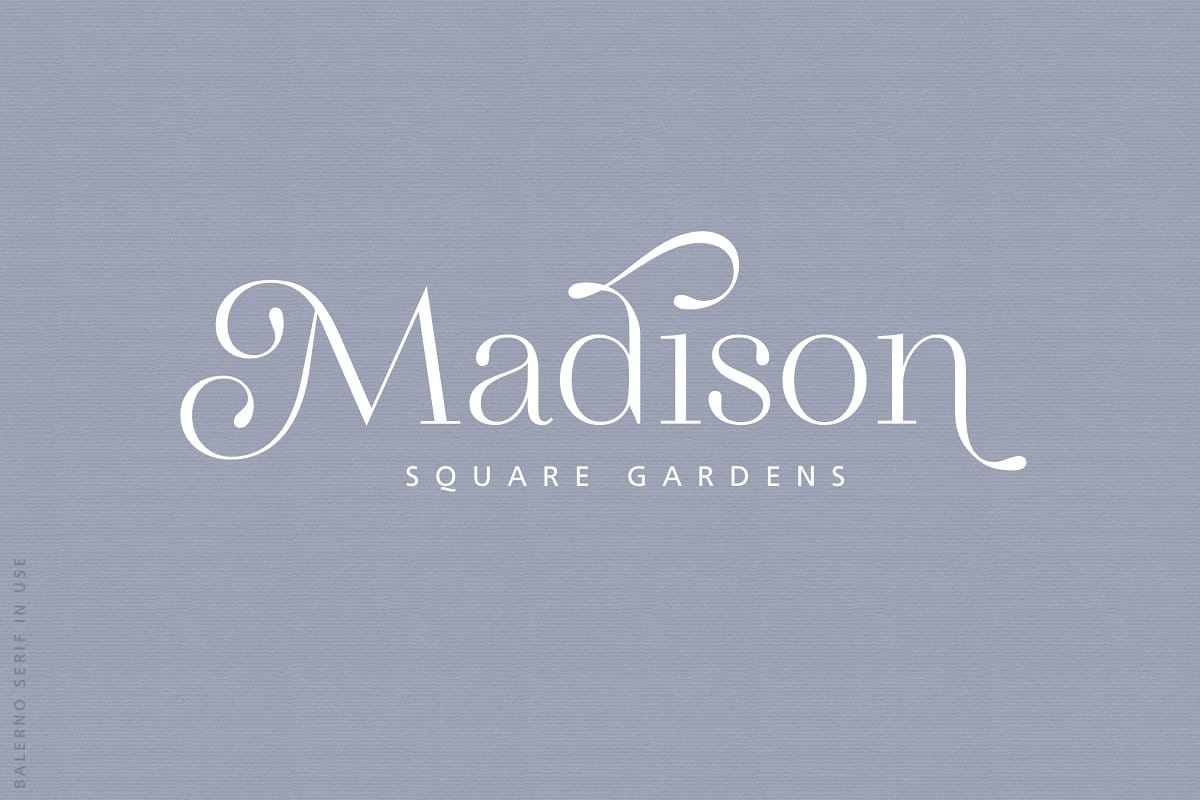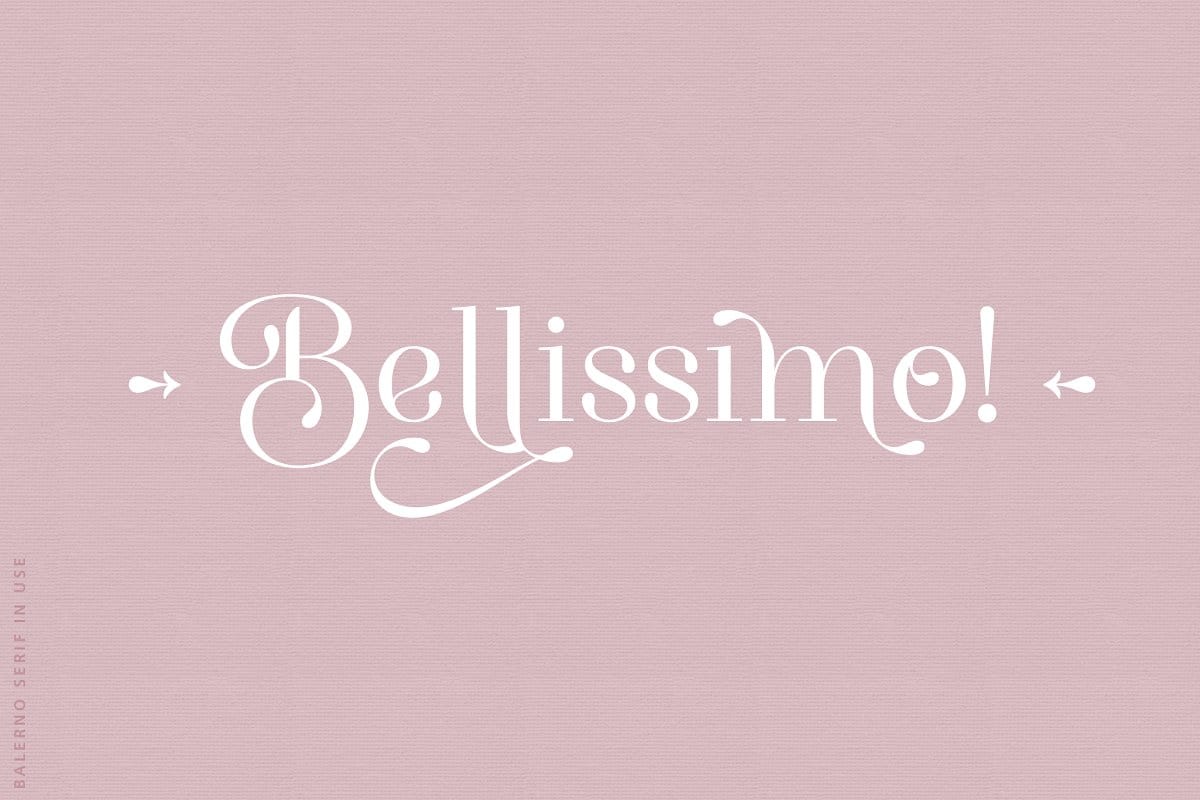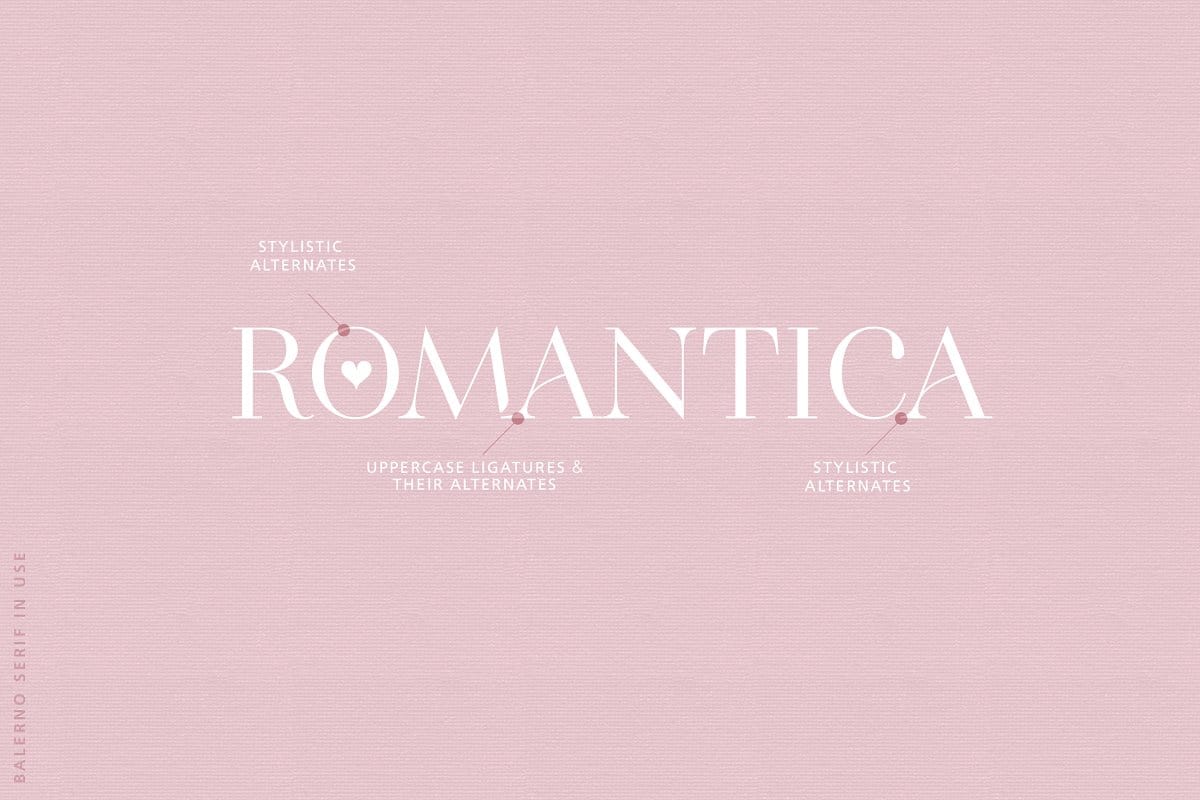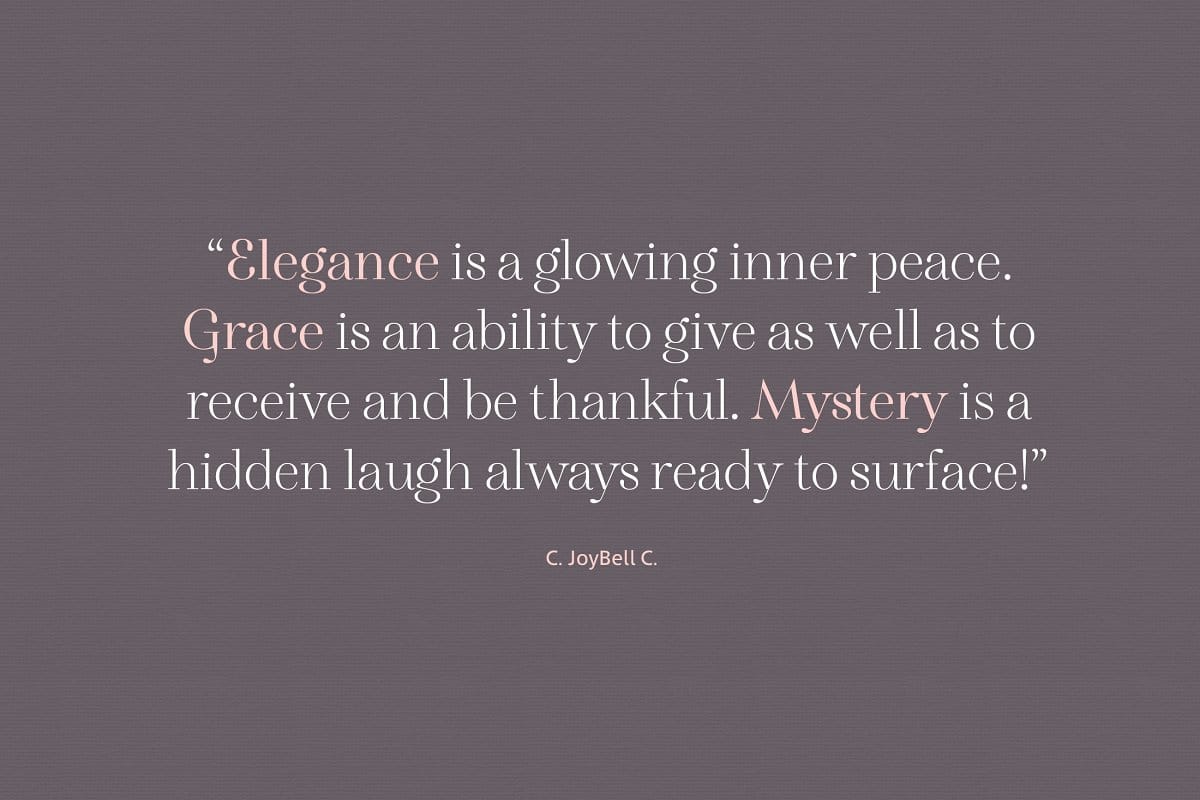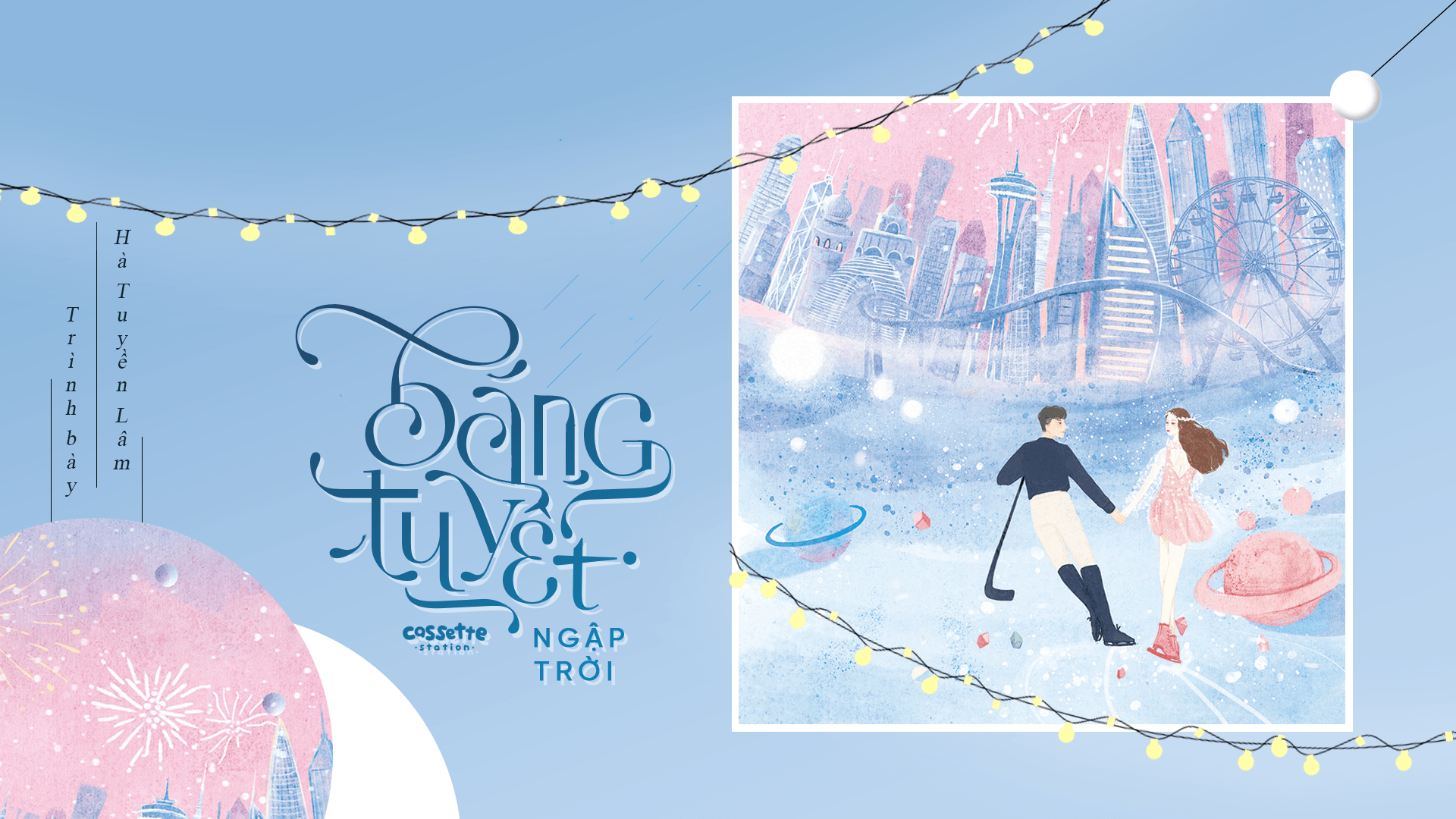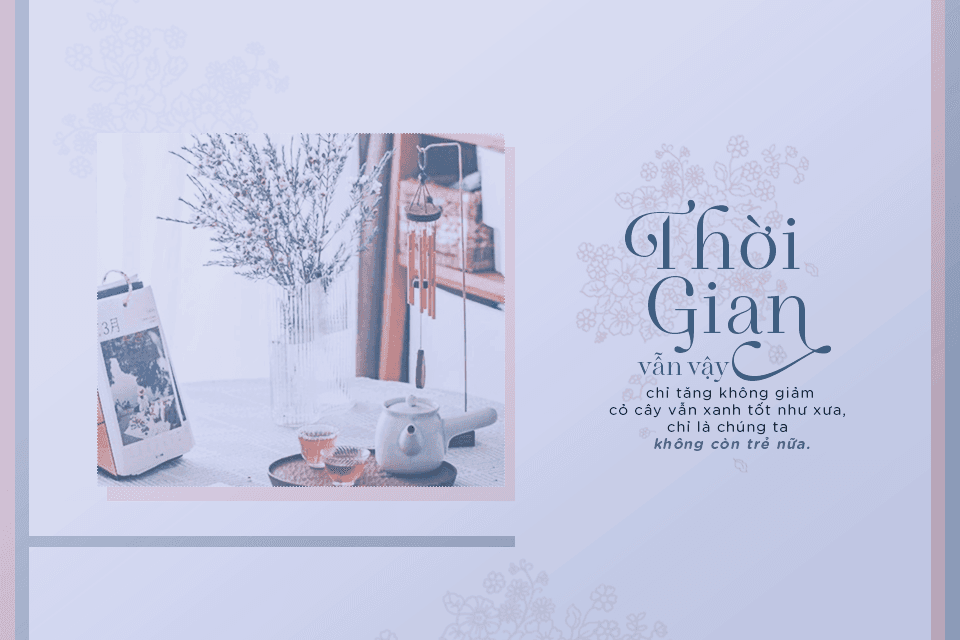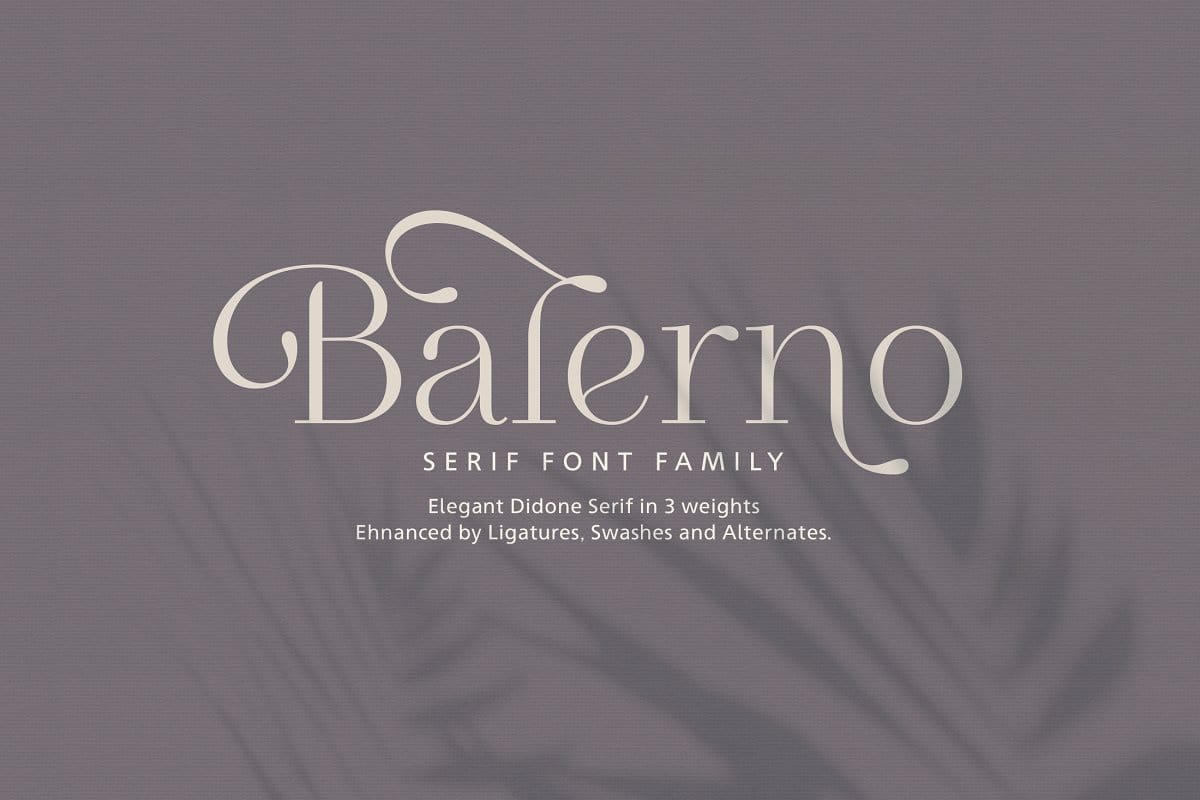
Balerno Serif là một font chữ hiện đại (nhưng cổ điển) được tăng cường bởi các chữ ghép, các chữ xen kẽ và dấu gạch chéo. Font Balerno Việt Hóa là một bộ font chữ rất linh hoạt – với các hình thức cổ điển và các tính năng hiện đại, nó bao gồm một loạt các dự án thiết kế bắt đầu từ thiệp chúc mừng đến tạp chí, lời mời đám cưới đến trang web, v.v.
Số lượng các thay thế là rất lớn, từ thay thế theo phong cách đơn giản đến các dấu ngoặc kép, chữ ghép và các thay thế của chúng.